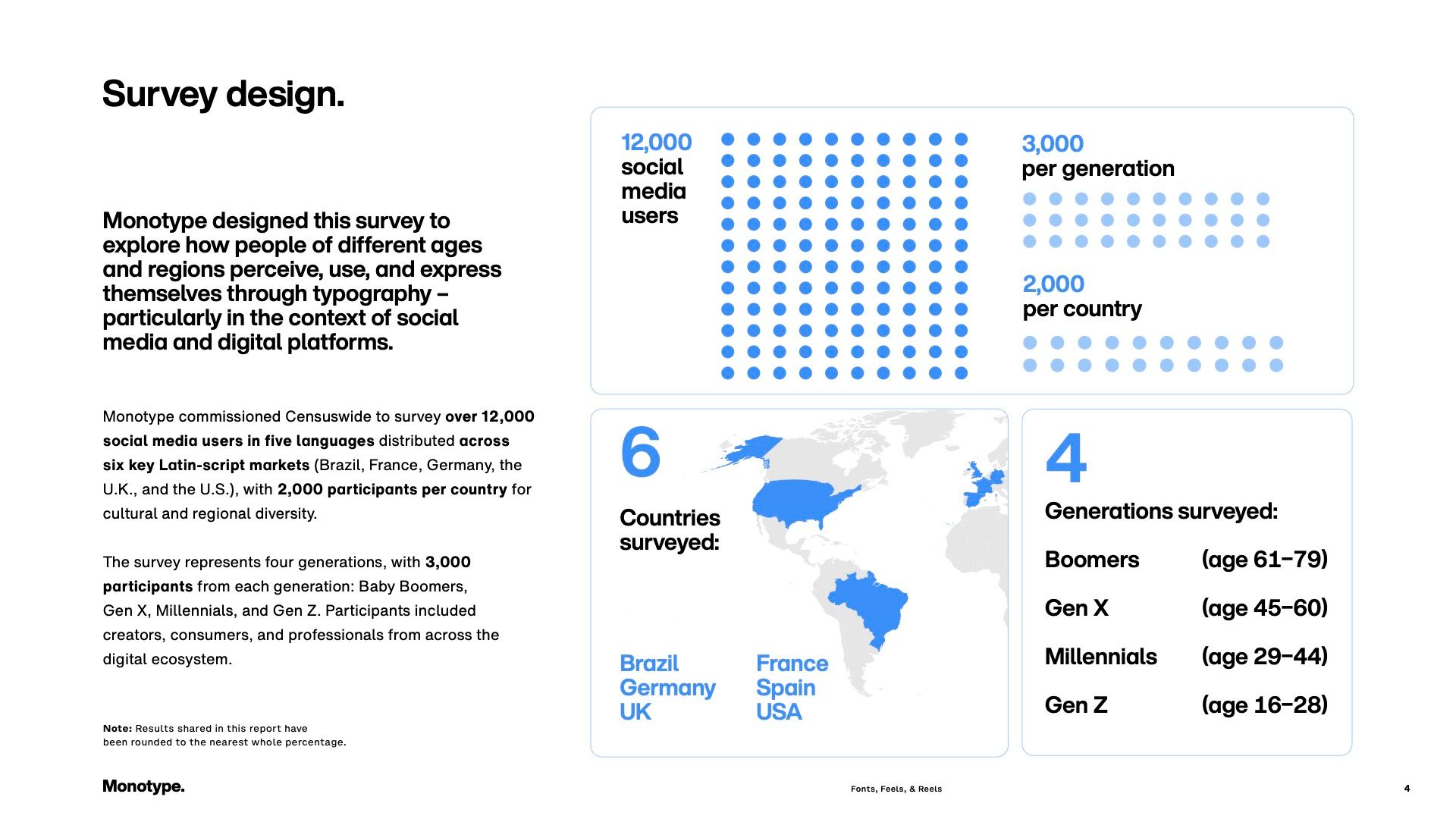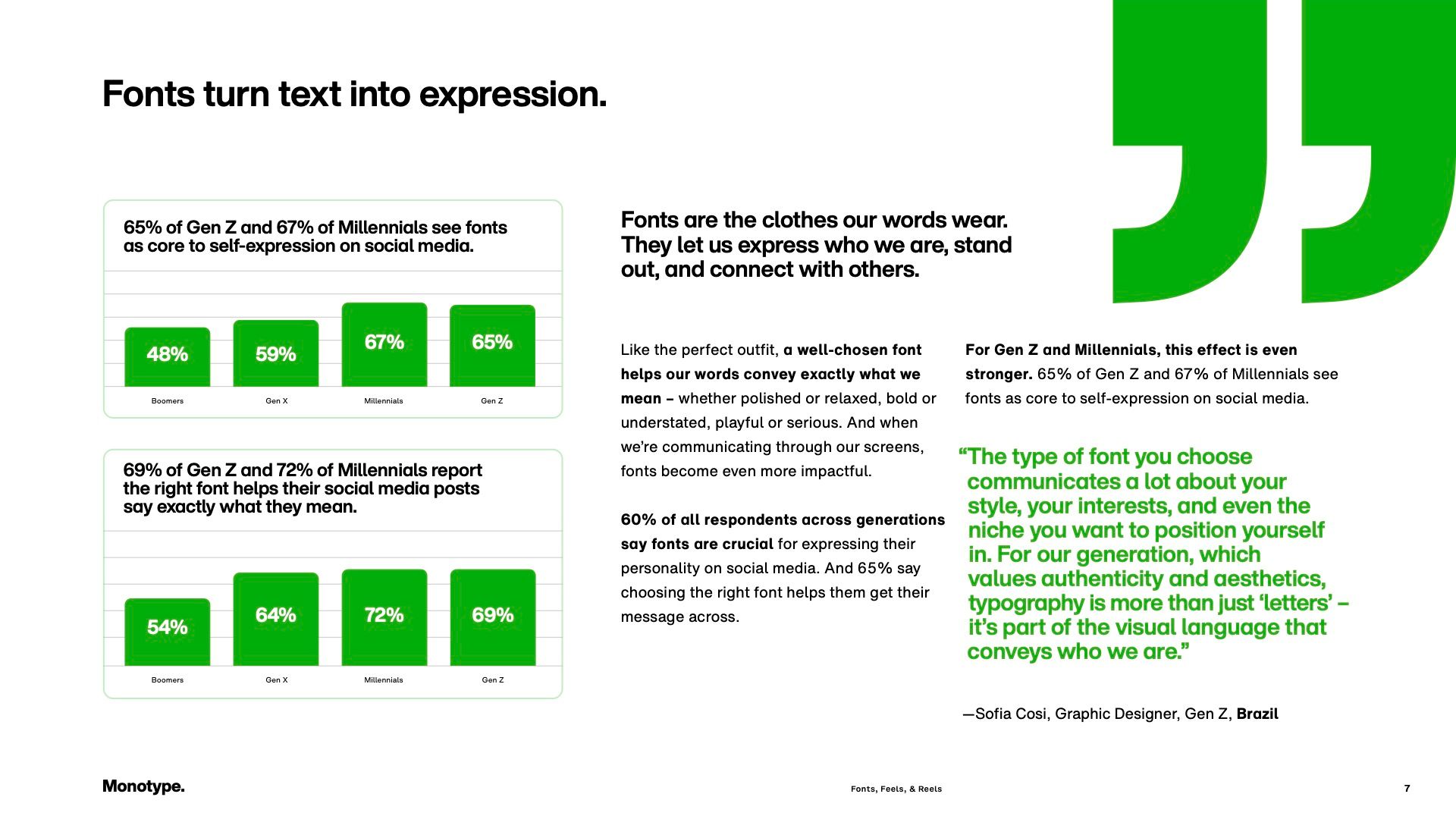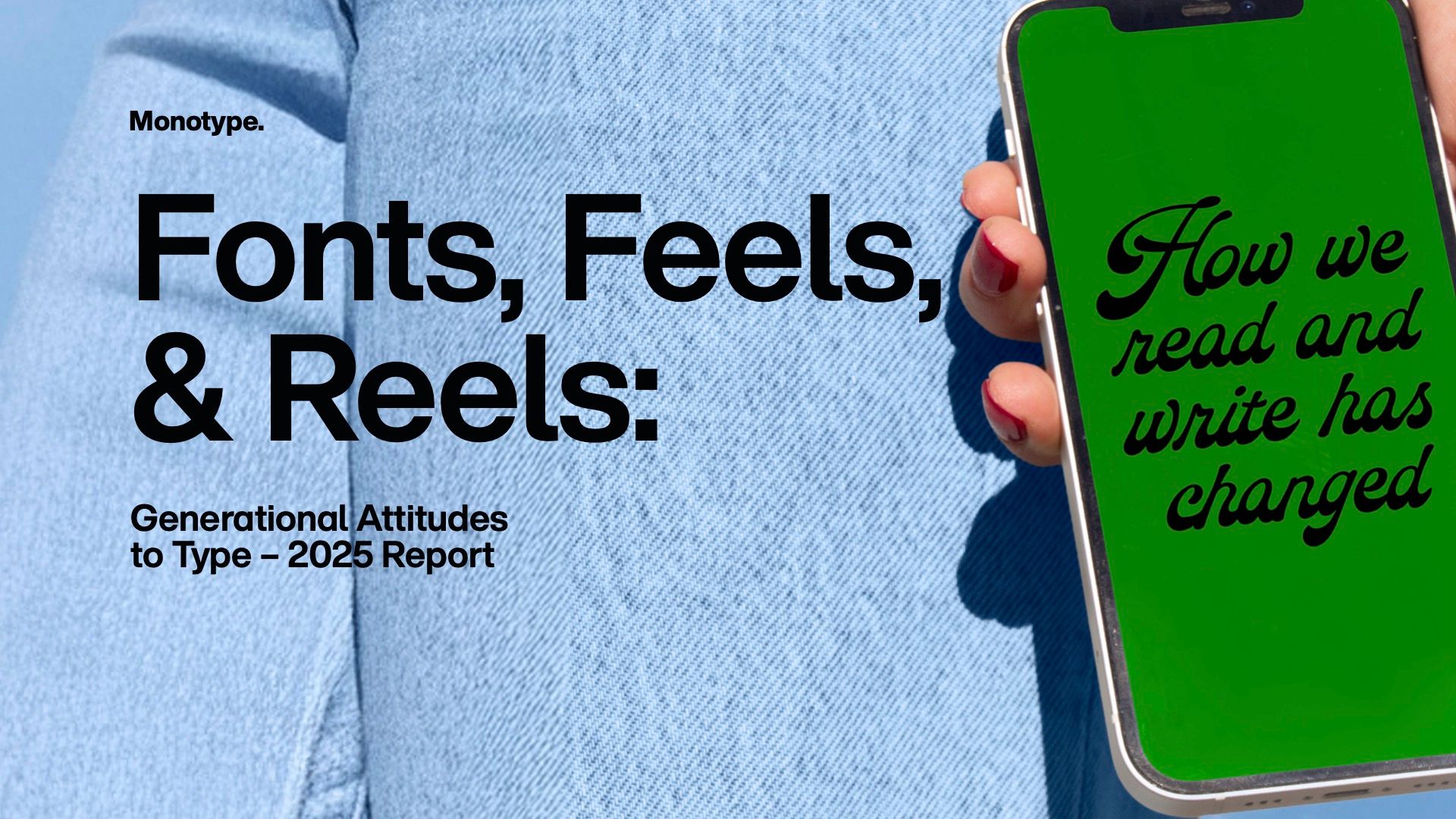
타이포그래피와 세대의 연속성.
타이포그래피는 단순한 글자 디자인을 넘어, 생각을 표현하고 정보를 전달하며 문화를 이어주는 중요한 시각적 언어입니다.
2025 서체 트렌드 보고서 Re:Vision에서는 기술이 서체의 디자인과 활용 방식에 어떤 영향을 지속적으로 미쳐왔는지를 탐구합니다. 특히 오늘날 소셜 미디어는 이러한 변화를 주도하는 핵심 요인으로, 우리가 소통하는 방식을 바꾸고 있습니다. 이를 통해 서체는 화면을 넘어 어조와 개성, 그리고 의미를 더욱 강하게 전달하는 수단으로 자리 잡고 있습니다.
새로운 보고서 '폰트, 감정, 릴스: 세대별 폰트 인식 2025'에서는 이러한 흐름을 한층 깊이 있게 분석합니다. 각 세대가 디지털 시대 속에서 서체를 어떻게 사용하고 어떤 가치를 부여하는지, 그리고 변화하는 커뮤니케이션 습관이 타이포그래피의 미래를 어떻게 이끌어갈지를 보여줍니다.
응답자의 78%는 독창적이고 상황에 맞는 폰트를 사용할 때, 소셜 미디어 게시물의 좋아요, 공유, 댓글 등 반응이 눈에 띄게 늘어난다고 답했습니다.
"이번 연구는 폰트 선택이 단순한 시각적 선택을 넘어, 세대 전반에 걸쳐 신뢰와 개성, 그리고 참여도에 직접적인 영향을 미친다는 점을 분명히 보여줍니다. 이는 브랜드와 플랫폼이 타이포그래피를 통해 어떻게 관객과 더 깊이 연결될 수 있는지를 보여주는 중요한 통찰을 제공합니다."
Tom Foley, Executive Creative Director, Monotype
이번 조사는 전문 업체 센서스와이드(Censuswide)와 협력해 진행되었습니다. 전 세계 6개국에서 베이비붐 세대부터 Z세대까지 총 12,000명을 대상으로, 그들이 소셜 미디어에서 어떻게 게시하고 창작하며 자신을 표현하는지, 그리고 주변에서 사용하는 폰트를 어떻게 인식하는지를 조사했습니다.
4개 세대와 6개 주요 라틴 문자권 시장의 소셜 미디어 이용자들이 폰트를 어떻게 인식하고 활용하는지, 그리고 그 결과가 디지털 플랫폼과 브랜드, 크리에이터의 미래에 어떤 의미를 가지는지 살펴보세요.
폰트의 중요성이 커지다
타이포그래피는 이제 디지털 소통의 중심이 되었습니다. 사람들은 폰트 선택이 콘텐츠의 인상과 참여도에 어떤 영향을 주는지 점점 더 민감하게 느끼고 있습니다.
폰트, 텍스트를 표현으로 바꾸다
각 세대는 소셜 미디어에서 타이포그래피를 자신을 표현하는 도구로 사용합니다. 선택한 서체를 통해 개성과 분위기, 정체성을 드러냅니다.
폰트, 참여를 이끄는 열쇠
적절한 폰트 선택은 참여율에 큰 영향을 줍니다. 사용하는 플랫폼에 따라 선호하는 서체 스타일과 반응이 달라집니다.
더 많은 폰트를 원한다
모든 세대가 디지털 플랫폼과 제작 도구에서 더 폭넓은 폰트 선택과 창의적인 활용을 원하고 있습니다.
첫인상은 폰트에서 시작
타이포그래피는 첫인상을 결정하는 핵심 요소입니다. 콘텐츠의 신뢰도와 호감도에도 직접적인 영향을 미칩니다.
세대마다 다른 폰트 인식
각 세대는 기술 환경과 소셜 미디어 경험에 따라 폰트를 인식하고 반응하는 방식이 다릅니다.